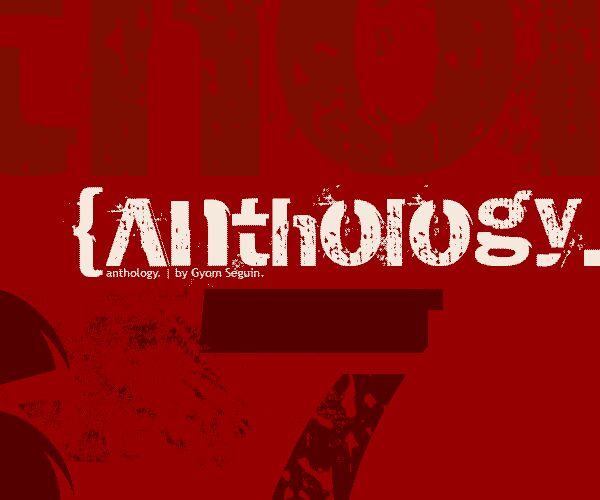
AnthologY od Gyomsegs to darmowy, erodowany krój typu display, który wygląda, jakby przeszedł przez tusz, beton i kserokopiarkę – i to w najlepszym wydaniu. Ciężkie, czarne litery są wyszczerbione, zachlapane i skorodowane, co nadaje każdemu słowu surową, namacalną fakturę. Połączenie grubych kresek i nieregularnych białych prześwitów sprawia, że nagłówki wyglądają na poobijane i sfatygowane, jakby przetrwały długą noc na miejskich murach.
Z AnthologY Twój tekst nie szepcze; on krzyczy z plakatów koncertowych, okładek albumów, tytułów horrorów, grafik streetwearowych, zinów i surowych okładek książek. Ten darmowy font najlepiej sprawdza się w dużych rozmiarach, gdzie jego poszarpane krawędzie i ziarnista powierzchnia naprawdę przebijają się przez tło. Połącz AnthologY z czystym, lekkim bezszeryfem w tekście głównym i pozwól temu erodowanemu krojowi zająć się krótkimi, mocnymi hasłami, które mają przyciągać wzrok.